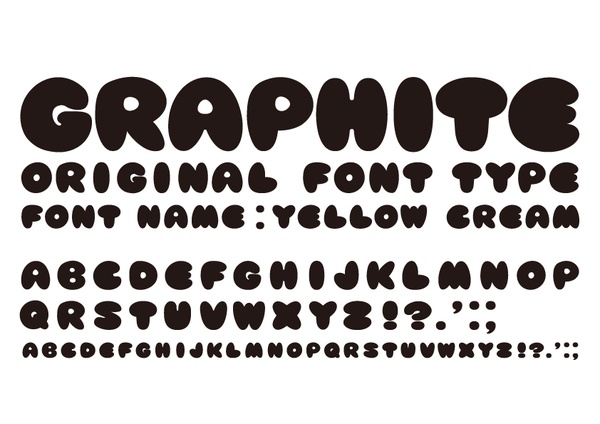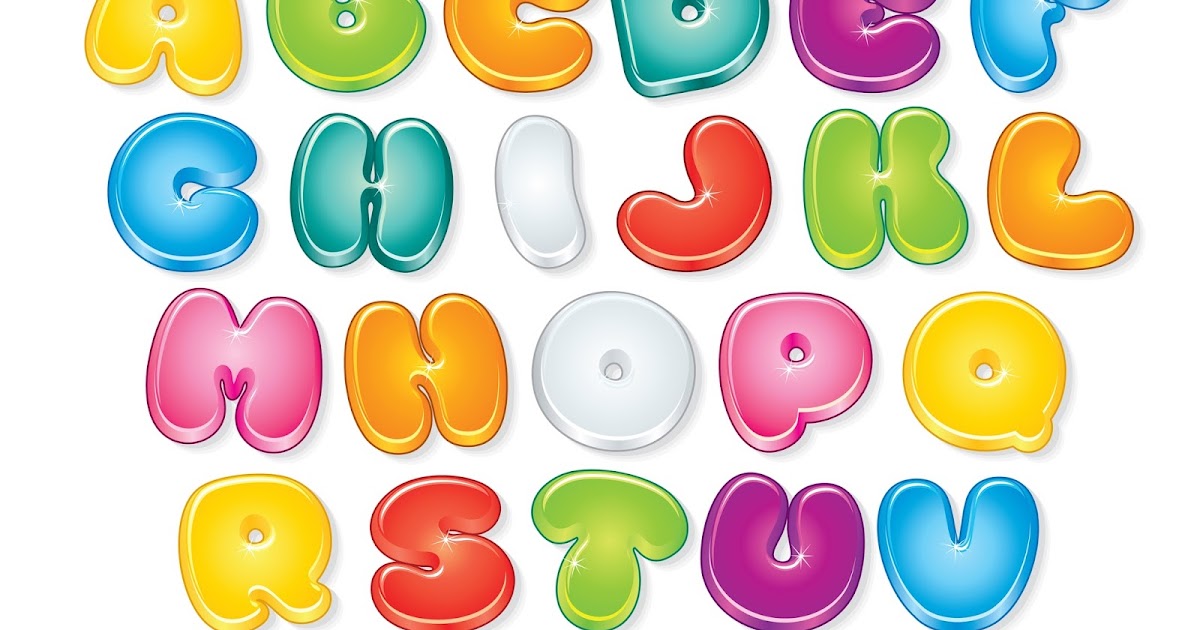
Шрифт круглый
Для любого проекта где необходим красивый текст или отдельные надписи, встает вопрос поиска актуальных шрифтов. Мы отобрали для вас наиболее популярные и уникальные типы округлых шрифтов, способные стать отдельным дизайнерском решением или влиться в их комплекс. Все гарнитуры символов поддерживают русские кириллические буквы и латиницу, обладают элегантностью и гармоничностью, их контуры спроектированы до мельчайших деталей.
Представленные круглые шрифты имеют собственные художественные достоинства, служащие для создания целостного образа полиграфический продукции. Их приятно и удобно читать, но не следует забывать о необходимости соответствия символов их предназначению — немногие из округлых гарнитур будут уместными в онлайн-индустрии из-за своей усложненности и формату межсловных или межстрочных пробелов.
Fonseca Rounded
Fonseca — популярный шрифт в стиле ар-деко, а Fonseca Rounded представляет собой хорошую альтернативу для немного другого вида. Он идеально подходит для винтажных проектов, таких как плакаты, листовки, реклама, футболки и многое другое.
Lucy Rounded